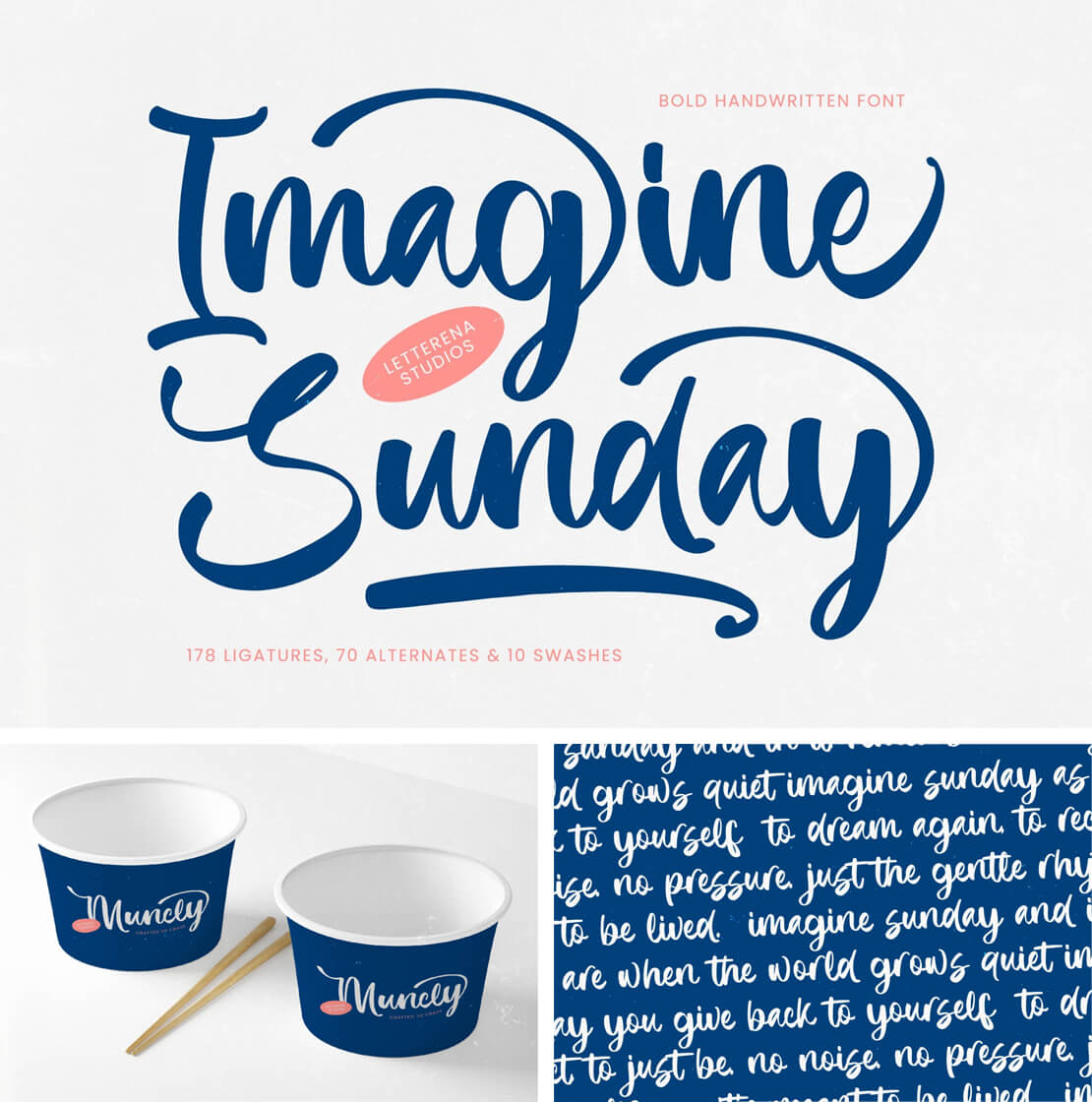
Imagine Sunday
Eine elegante Script-Schrift mit handgeschriebenem Charakter und leichtem Retro-Touch. »Imagine Sunday« gibt es in den Schnitten »Regular« und »Italic« zum Downloaden.
Die Schrift wird im Opentype-, Truetype- und Webfont-Format angeboten und enthält Alternativzeichen sowie Ligaturen. Auch Umlaute und weitere Sonderzeichen sind enthalten.